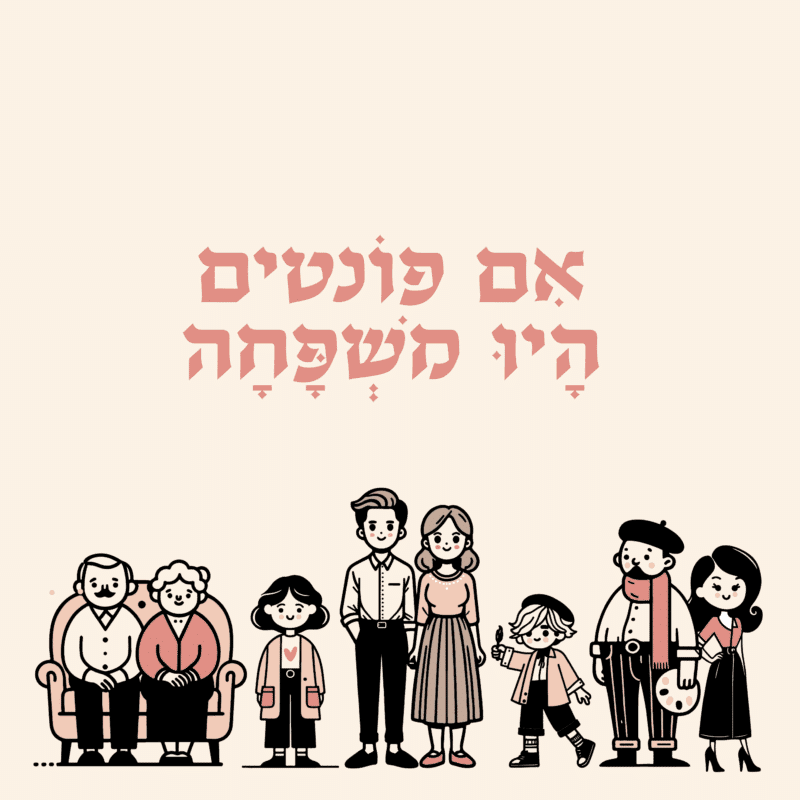
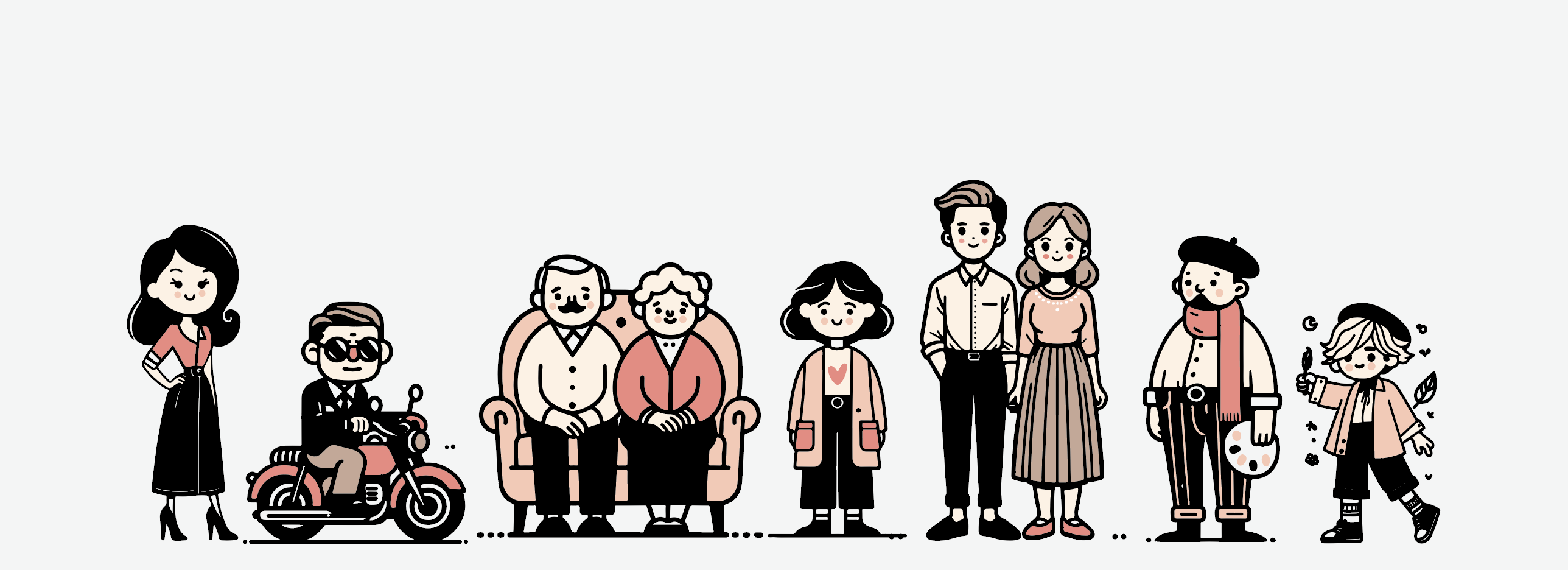
וכמו לכל משפחה, לכל אחד מסוגי הפונטים יש את האישיות והתפקידים הייחודיים שלו. הבנת הקטגוריות השונות של הגופנים והמאפיינים שלהם יכולה לעזור למעצבים לבחור את הגופן המתאים לכל פרויקט, וליצור עיצובים פונקציונליים ואסתטיים כאחד.
במאמר זה, נחקור את משפחת הגופנים ואת האישיות הייחודית שלהם. הצטרפו אלינו כשאנחנו צוללים לתוך העולם המרתק של הטיפוגרפיה ומגלים מה יש לכל פונט להציע.
גופני סקריפט הם הדודה המגונדרת שתמיד נראית כאילו היא בדיוק יצאה מסלון יופי.
גופני סקריפט הם כמו הדיוות של הטיפוגרפיה, שנועדו להביע אמירה ולהתבלט. הגופנים האלה בדרך כלל מלאים בקישוטים וסווישים, עם אותיות שיוצאות מהקווים בצורה מוגזמת. הם יכולים להיות אלגנטיים ורשמיים, עם עובי קו משתנה שגורמים להם להיראות כאילו נכתבו הרגע על ידי קליגרף, או שובבים וגחמניים, כמו משהו שהייתם משרבטים בשולי המחברת באיזה הרצאה משעממת.
גופני סקריפט מגיעים בכל הצורות והגדלים, אבל לכולם יש דבר אחד במשותף: הם נועדו להיראות כמו כתב יד או קליגרפיה עברית. ובדיוק כמו כתב יד, הם יכולים לחשוף הרבה על האדם שכתב אותם. גופני סקריפט מסוימים הם נועזים ובטוחים, אחרים עדינים ומאופקים.
חלקם מודרניים ונוכחים, בעוד שאחרים קלאסיים ונצחיים. אז, אם אתם מעצבים הזמנות לחתונה, יוצרים לוגו לעסק, או סתם רוצים להוסיף נופך של רומטניקה לפרויקט הבא שלכם, גופן סקריפט יכול להיות מתאים. אבל זהירות – בדיוק כמו דודה הפנסית שלך, גופני סקריפט יכולים להיות מעט טו מאץ׳ לפעמים. והם לא תמיד הבחירה הנכונה.
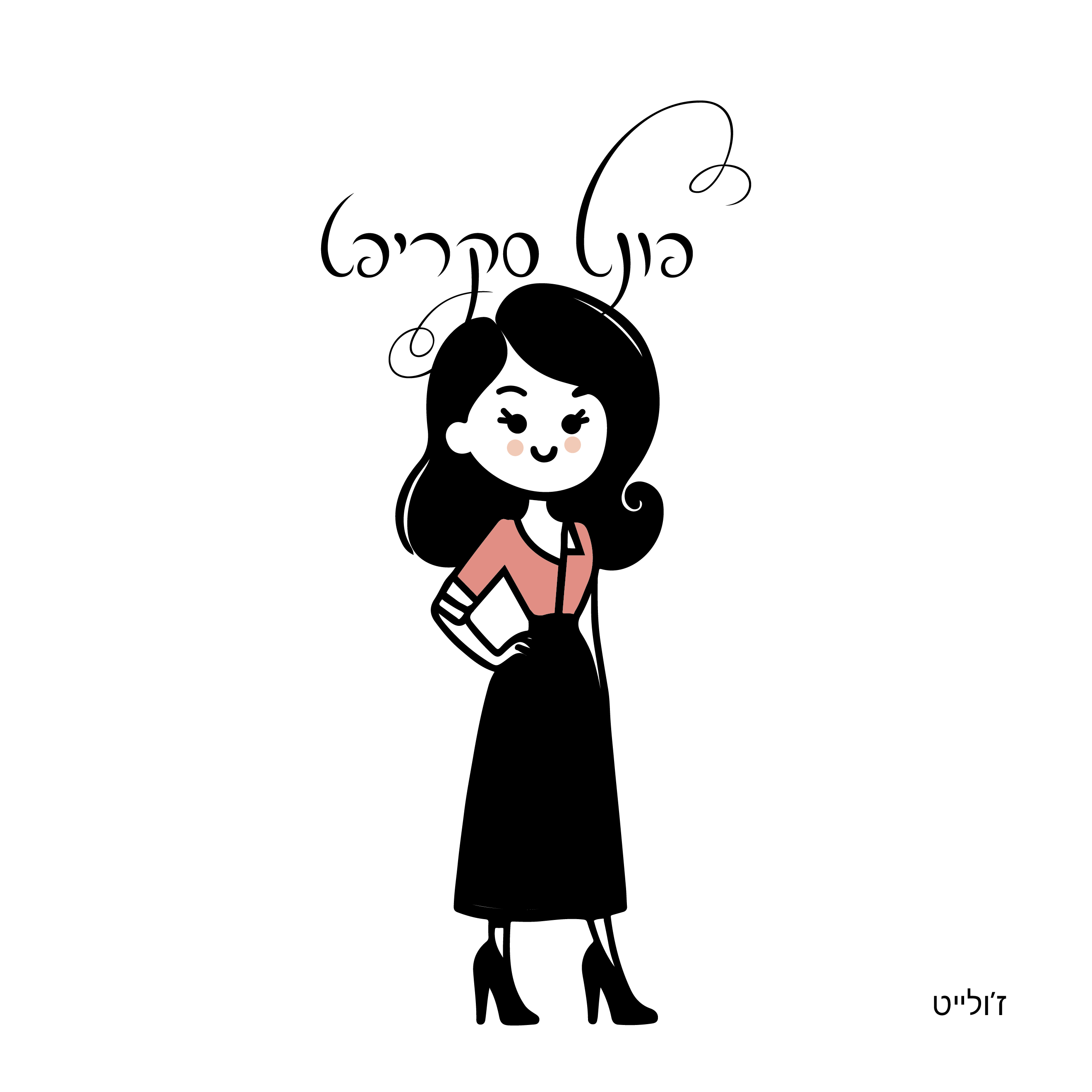
גופני סלאב סריף הם הדוד המגניב עם מעיל העור והאופנוע. גופני סלאב סריף הם סוג של אותיות עם סריפים מודגשים ומלבניים בעובי כמעט זהה או זהה לעובי האות עצמה. הם מעניקים מראה מודרני, אסרטיבי ונוכך. גופני Slab Serif הם רב-תכליתיים וניתן להשתמש בהם במגוון רחב של עיצובים, החל מעיצוב אתרים ועד מיתוג ועיצוב אריזות.
הם יכולים להעביר מצבי רוח וסגנונות שונים בהתאם למשקל ולצורה. ניתן להשתמש בהם כדי להוסיף תחושת חוזק ויציבות לעיצוב, או ליצור תחושת ניגודיות ומתח. הם אולי לא ראוותניים כמו גופני סקריפט, אבל הם מפצים על זה עם האישיות הנועזת והתקיפה שלהם.
אז, אם אתם מחפשים להוסיף וויב מגניב ומודרני לפרויקט הבא שלכם עם פונטים בעברית לשימוש מסחרי, גופן סלאב סריף בהחלט יכול לעשות את העבודה.
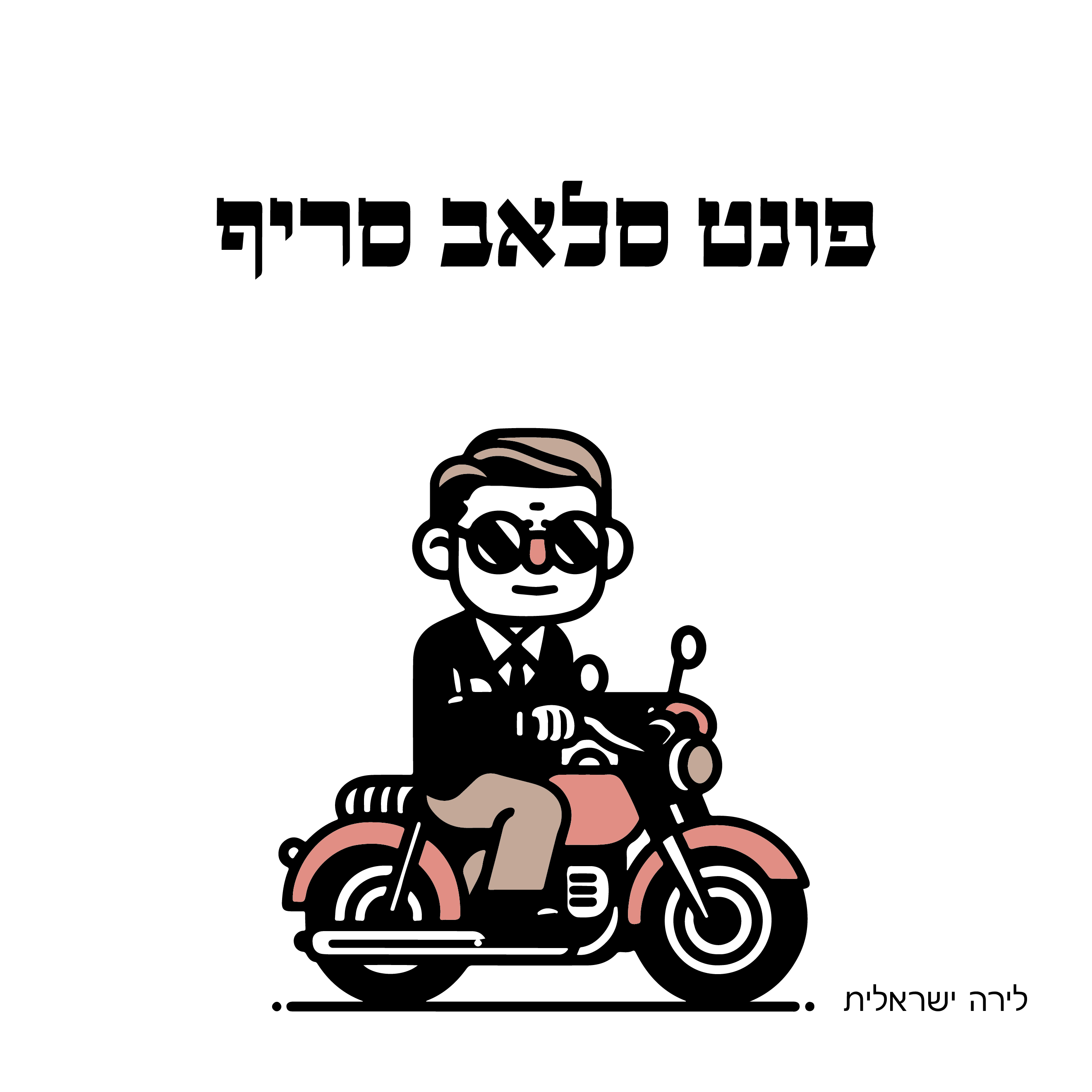
ההורים היציבים והאמינים
גופני סנס סריף הם סוג של גופן שאין לו את השפיצים הקטנים בקצה האות שנקראים "סריפים". (סנס בצרפתית = ללא)
זה מקנה להם מראה נקי ומודרני, מה שהופך אותם לבחירה פופולרית עבור מגוון רחב של עיצובים, מממשקי אינטרנט ומובייל ועד לוגואים ושילוט. גופנים ללא סריף מקושרים לרוב למודרניזם, מינימליזם ופשטות. הם מגיעים במגוון משקלים וסגנונות, מדקים ועדינים ועד נועזים ומשפיעים. הם יכולים להעביר מצבי רוח ואישיות שונים בהתאם למשקל, לצורתם ולריווח שלהם. הם אולי לא ראוותניים כמו גופני סקריפט או כוחניים כמו גופני סלאב סריף, אבל הם מפצים על זה עם האיכויות הנצחיות והאמינות שלהם. לכן, אם אתם מחפשים גופן פשוט, מודרני ואמין, גופנים סנס סריפיים עשויים להיות הבחירה הנכונה לפרויקט הבא שלכם.
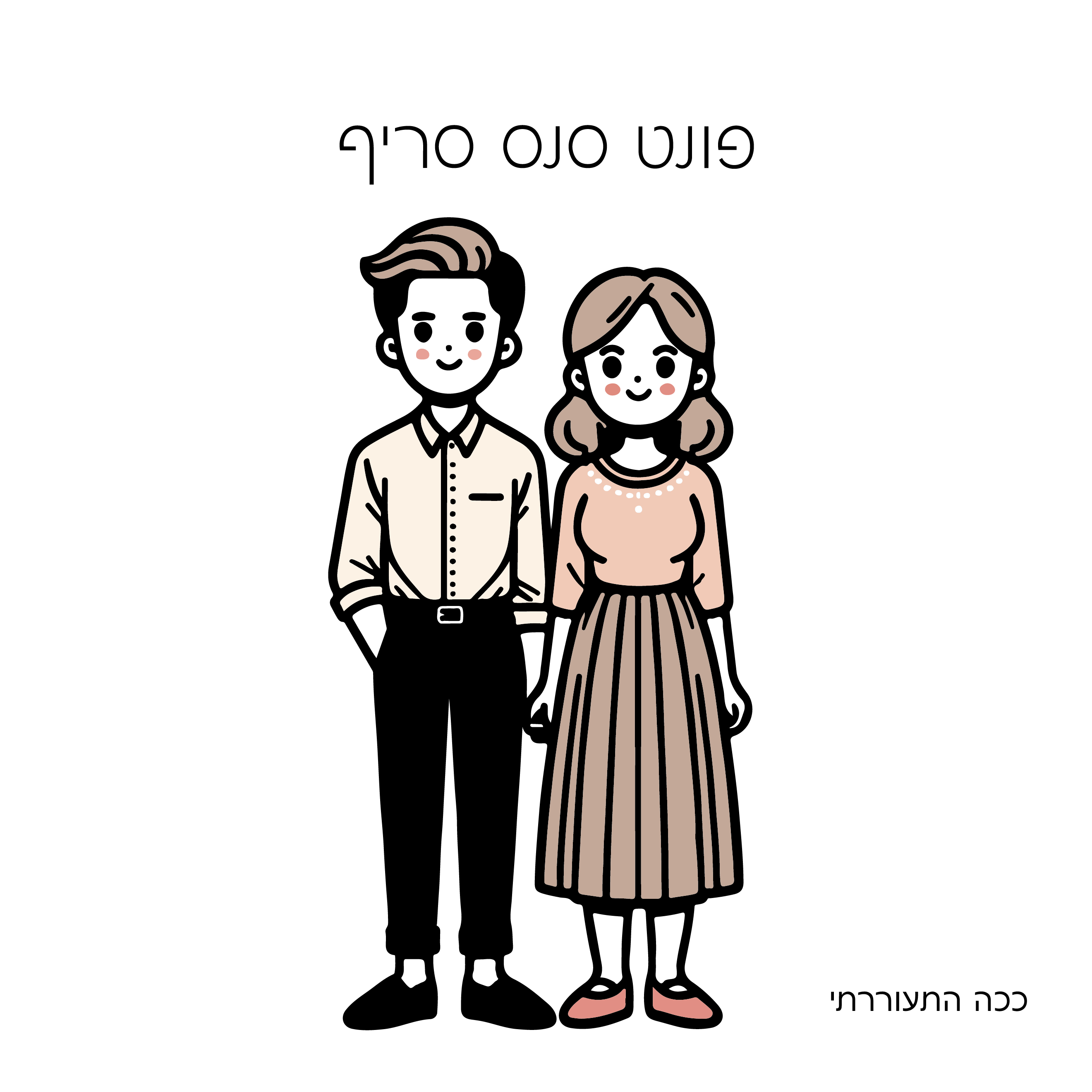
הילד המשורר הגחמני והחופשי במשפחת הפונטים.
גופנים בכתב יד משמשים לעתים קרובות בעיצובים שדורשים מגע אישי או לא רשמי, למשל כרטיסי ברכה, הזמנות או בלוגים אישיים. הם יכולים לשמש גם כדי להעביר תחושת יצירתיות או שובבות בעיצובים למוצרי ילדים, כמו גם במיתוג ופרסום של מוצרים שמטרתם להיות נגישים וידידותיים.
אחד היתרונות המרכזיים של גופנים בכתב יד הוא שהם יכולים להוסיף תחושה של אותנטיות וכנות לעיצוב. הם יכולים לגרום לטקסט להיראות כאילו הוא נכתב ביד, מה שיכול ליצור קשר עם הצופה ולהוסיף מגע אישי שלעיתים חסר בעיצובים סטריליים או מכניים יותר.
אז אם אתם מחפשים להוסיף מגע אישי לפרויקט הבא שלכם או ליצור עיצוב שובב ויצירתי, גופנים בכתב יד יכולים להיות בחירה מצוינת.
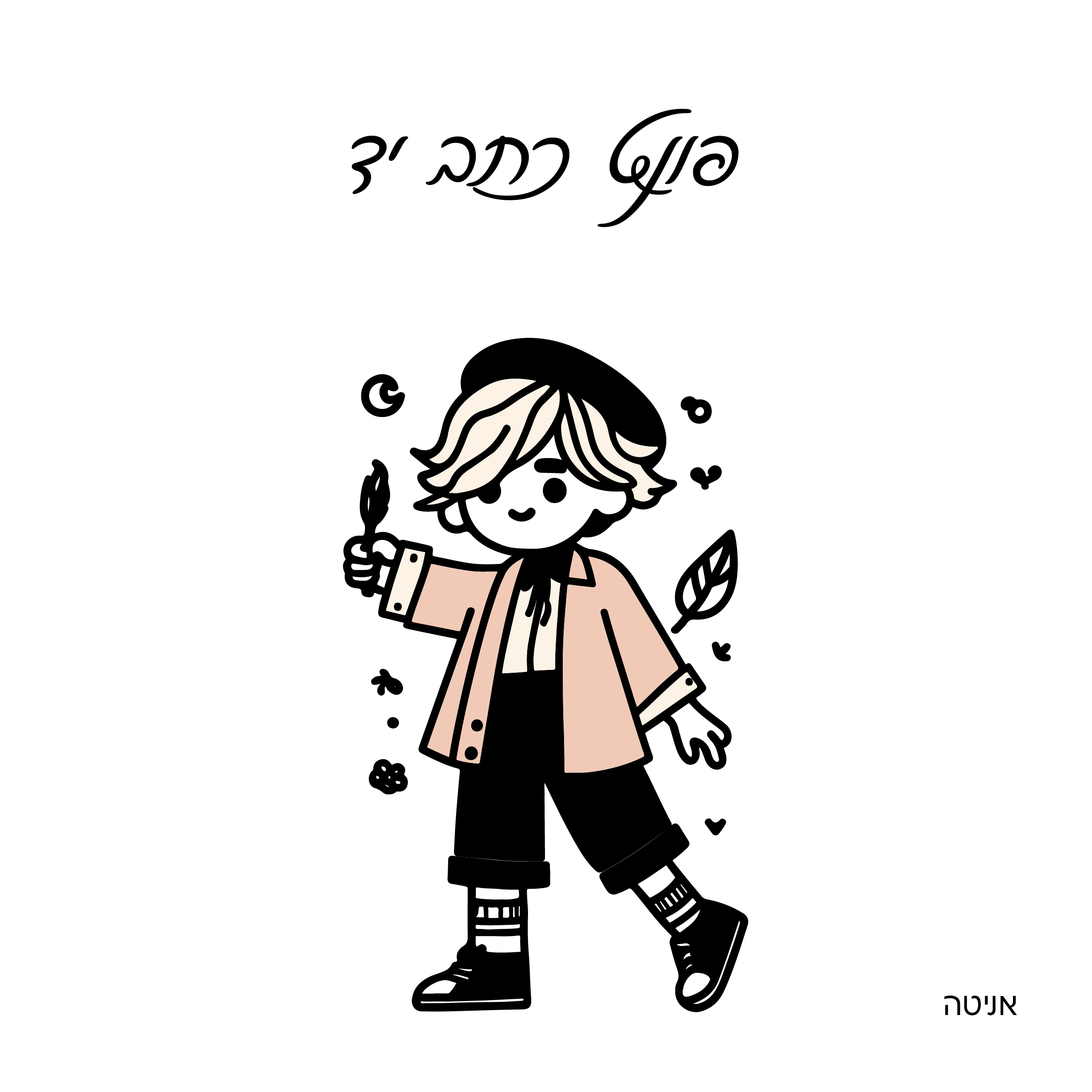
הדוד המוזר והאומנותי במשפחת הפונטים.
הדוד המוזר והאמנותי במשפחת הגופנים. פונט דיספליי הוא סוג של גופן שעוצב במיוחד לשימוש בגדלים גדולים יותר, כגון כותרות גרנדיוזיות או שילוט חוצות. לעתים קרובות הם דקורטיביים מאוד ויש להם צורות ייחודיות ומשוכללות שגורמות להם לבלוט מגופנים אחרים.
הם משמשים לעתים קרובות כדי ליצור השפעה חזותית מובהקת בעיצוב ויכולים להיות דרך מצוינת להוסיף אישיות ויצירתיות לפרויקט. אחת התכונות המרכזיות של גופני תצוגה היא שהם נועדו למשוך תשומת לב, כך שהם יכולים לעזור לבסס היררכיה ויזואלית חזקה בעיצוב. הם משמשים לעתים קרובות במיתוג, פרסום ועיצוב כדי ליצור מראה ותחושה ייחודיים שמייחדים את העיצוב מאחרים. למרות שהם אולי לא מעשיים או מגוונים כמו גופני סריף או סנס סריף, הם יכולים להיות כלי רב עוצמה ליצירת עיצוב ייחודי ובלתי נשכח. לכן, אם אתם מחפשים גופן מודגש, יצירתי ומושך תשומת לב, גופני דיספליי עשויים להיות הבחירה המושלמת לפרויקט הבא שלכם.
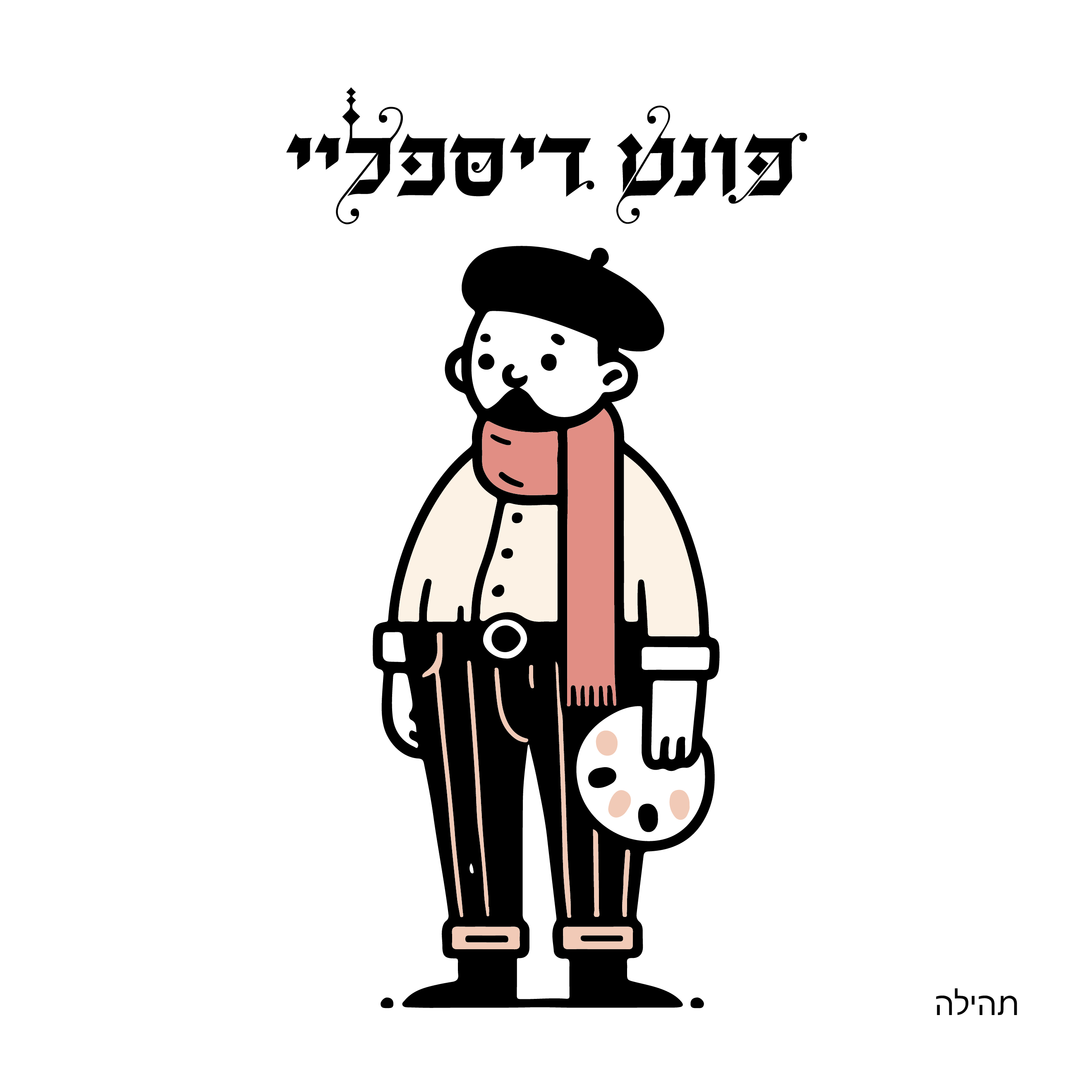
הסבים והסבתות הקלאסיים והמעודנים.
גופני Serif הם סוג של גופן בעל ״צ׳ופצ׳יקים״ קטנים בקצוות העליונות של האותיות. לעתים קרובות הם קשורים למסורת, לקלאסיקה ולרשמיות, אפשר לראות את השימוש הרחב שלהם בעיקר ביישומים מודפסים כמו ספרים, עיתונים ומגזינים. גופני סריף נועדו להיות קריאים בגדלים קטנים ובכמויות טקסט גדולות. גופני סריף נבחרים לעתים קרובות בשל האיכויות האלגנטיות והנצחיות שלהם, מה שיכול לעזור לבסס תחושת מסורתיות או סמכות בעיצוב. בסך הכל, גופני סריף הם גופנים רב תכליתיים ואמינים שניתן להשתמש בהם במגוון רחב של עיצובים, מחומרים מודפסים ועד ממשקים דיגיטליים. עם המראה הקלאסי והמעודן שלהם, גופן סריף עשוי להיות הבחירה טובה לפרוייקט שדורש קריאות גבוהה בעיקר בחומרים מודפסים.
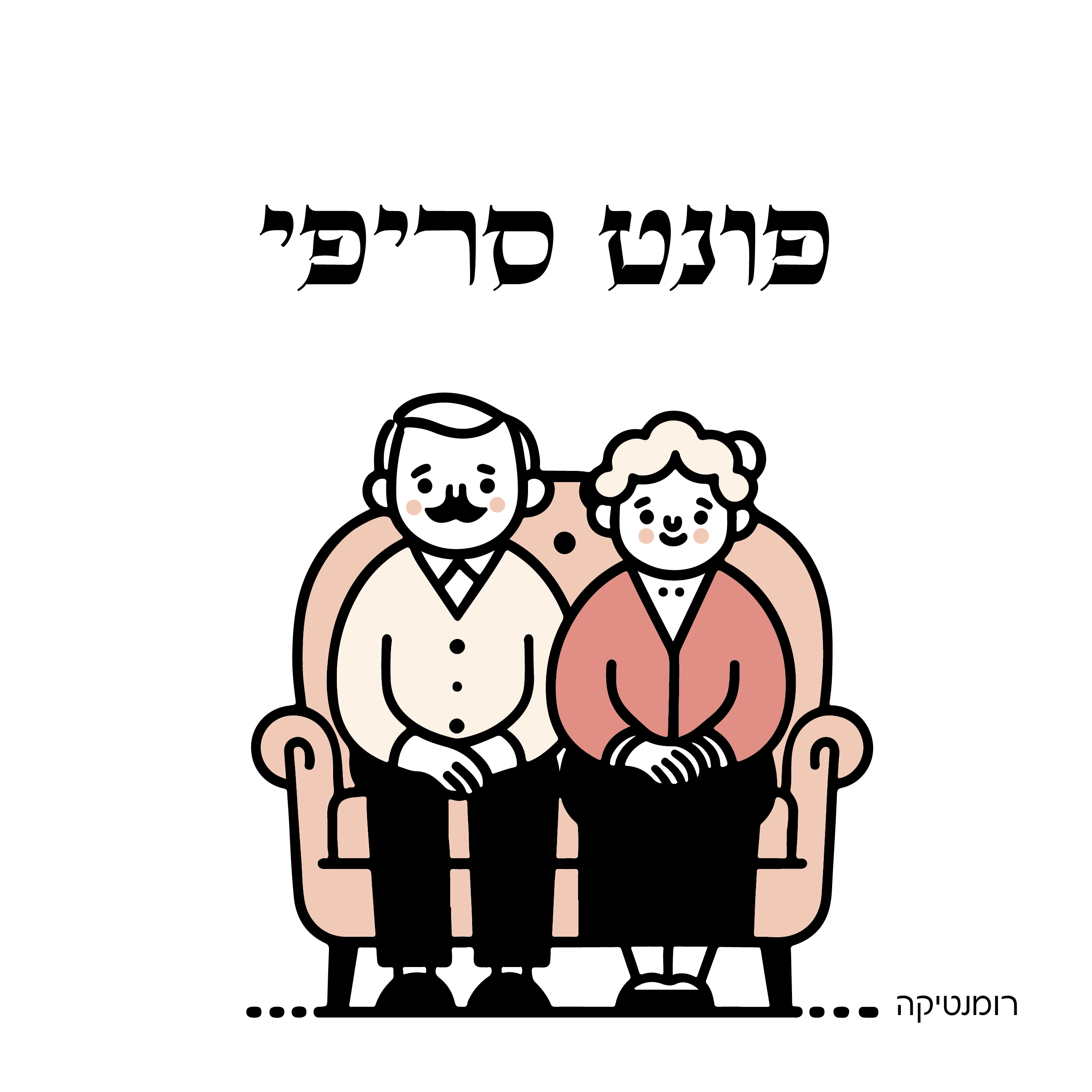
האחות הבכורה הדואגת והחומלת
פונטים הומניסטיים נשענים בדרך כלל על בסיס של פונטים מסורתיים יותר. הם נועדו להיות קריאים ונגישים, ולתת תחושת חמימות או נוסטלגיות. כמו אחות מבוגרת, גופנים הומניסטיים הם אמינים ונעימים. הם משמשים לעתים קרובות בעיצובים הדורשים גוון ידידותי וקריא כמו חומרים חינוכיים, ספרי ילדים ומוצרי בריאות ואיכות חיים. גופנים הומניסטיים משמשים גם עבור ממשקי משתמש, אפליקציות ואתרי אינטרנט, מכיוון שהם יכולים להפוך את הטקסט לנגיש יותר וקל יותר לקריאה. לסיכום, הגופן ההומניסטי הוא גופן רב תכליתי וידידותי ויכול להוסיף נופך של חמימות ונגישות לכל עיצוב.
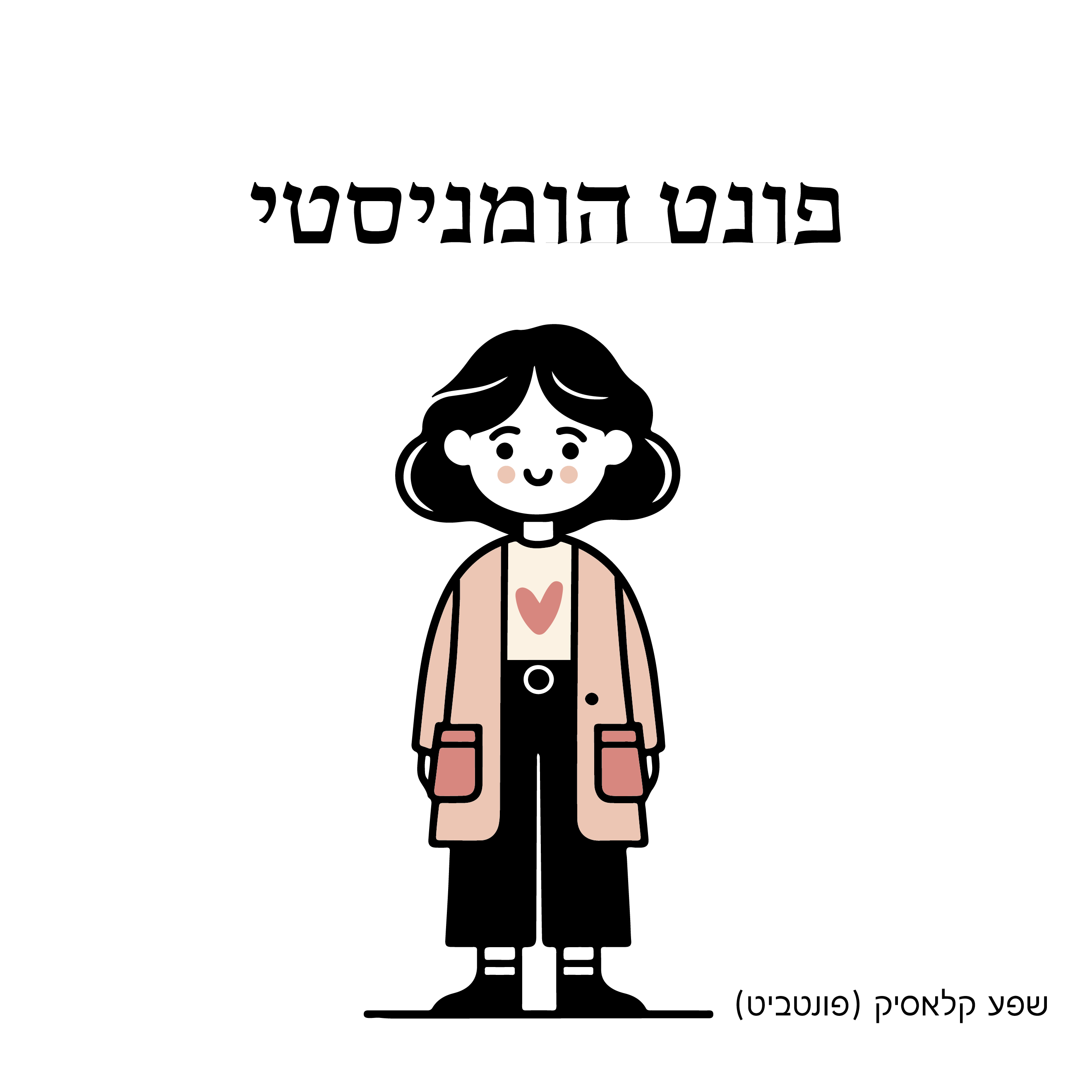
הכוונה היא לדמיין פונטים בעברית להורדה כדמויות במשפחה, כאשר כל פונט מייצג אישיות ותכונות מסוימות, מה שמאפשר להבין ולהתחבר לפונטים בצורה יצירתית וכיפית.
כל פונט יכול להיות מקושר לתכונות מסוימות. למשל, פונט סריפי מסורתי יכול לייצג את הסבא, בעוד פונט מודרני ונקי יכול להיות הדמות של הילד הצעיר והחדשני במשפחה.